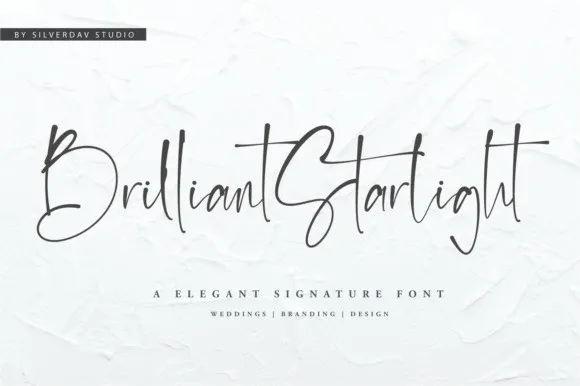
Brilliant Starlight Script Font – Download Grátis
Introduzimos uma nova fonte script elegante chamada Brilliant Starlight Font. Esta é uma fonte escrita a mão que é perfeita para personalizar qualquer projeto de design. Ela transmite genuíno autenticidade e pode transformar seu trabalho em algo único, destacando-se dos demais. Perfeito tanto para projetos de marca como para designs de casa, embalagens de produtos ou cartões de nome ou convite, esta fonte script é a escolha perfeita. Ela tem um brilho intenso que vai ao encontro do seu design e dará vida à sua obra de arte. Use-a para criar algo impressionante e único. Brilliant Starlight Font traz uma atmosfera hipnotizante, ideal tanto para aqueles buscando expressar genuíno autêntico em um projeto quanto para os criativos que desejam dar a seus designs um toque especial. Através da linguagem deste fonte, você pode criar algo verdadeiramente único e memorável.